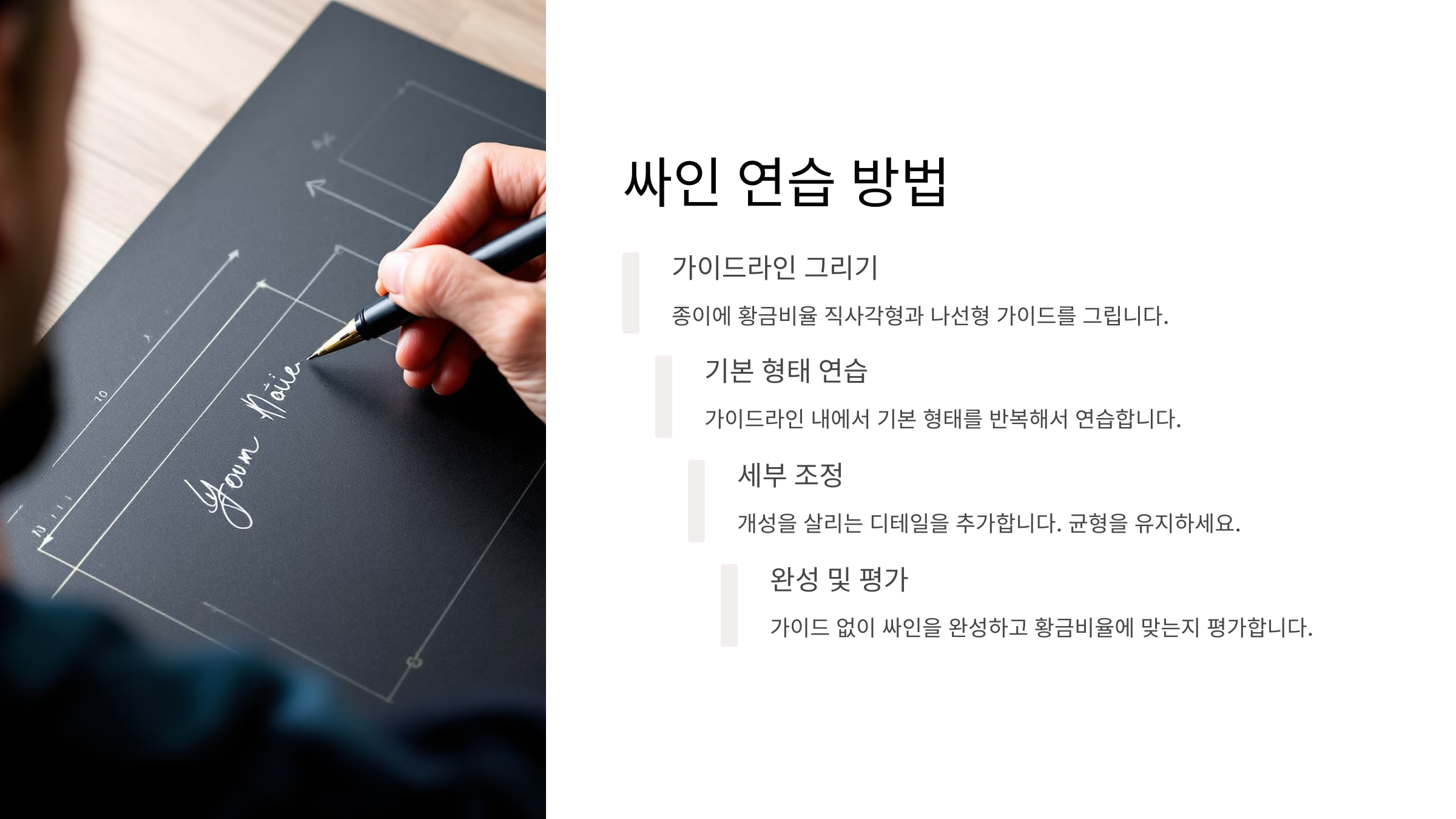
싸인도 디자인처럼 비율과 균형을 맞추면 더 멋져 보일 수 있어요! ✨ 특히 황금비율(1:1.618)을 활용하면 자연스럽고 조화로운 싸인을 만들 수 있죠. 🖊️
싸인이 너무 크거나 작으면 언밸런스해 보일 수 있고, 글자 간격이 너무 좁거나 넓으면 가독성이 떨어질 수 있어요. 그래서 싸인의 디자인 원칙을 알고 적용하는 것이 중요해요! ✅
그럼, 먼저 싸인의 황금비율이란 무엇인지부터 알아볼까요? 🔍
싸인의 황금비율이란? 📐
싸인의 황금비율이란 자연스럽고 균형 잡힌 서명을 만들기 위한 비율 원칙이에요. 우리가 흔히 알고 있는 1:1.618의 황금비율을 적용하면, 싸인도 훨씬 조화롭고 세련되어 보여요! ✨
이 황금비율은 자연과 예술, 건축, 디자인 등에서 흔히 발견되는 비율인데요. 레오나르도 다빈치의 '비트루비우스 인간', 피라미드, 유명 로고 디자인에도 적용됐어요! 🏛️
📌 싸인에서 황금비율이 적용되는 요소 ✅
요소 설명 싸인의 전체 크기 너무 크거나 작지 않도록 적절한 비율 유지 (1:1.618 적용) 이니셜과 나머지 글자 비율 이니셜이 전체의 약 61.8%를 차지하면 균형이 맞음 글자 간격 너무 붙거나 멀지 않도록 황금비율 간격 유지 곡선과 직선 조화 부드러운 곡선과 직선적 요소를 황금비율로 배치 이 원칙을 적용하면 더 세련되고 균형 잡힌 싸인을 만들 수 있어요! 그럼 이제, 싸인의 균형을 맞추는 방법을 알아볼까요? ⚖️
균형 잡힌 싸인 만들기 ⚖️
싸인이 멋지게 보이려면 균형이 맞아야 해요. 너무 기울거나, 글자가 한쪽으로 몰리면 비대칭적인 느낌이 들어요. 적절한 비율과 배치를 고려하면, 조화로운 싸인을 만들 수 있어요! ✅
📌 균형 잡힌 싸인을 위한 4가지 요소 🎯
요소 설명 예시 1. 중심축 맞추기 싸인의 중심이 기울지 않도록 일정한 축을 유지 "J.Kim" → J와 K를 동일한 높이로 정렬 2. 글자 크기 조정 이니셜이 너무 크거나 작지 않도록 황금비율로 조절 "H.Park" → H가 전체의 61.8% 차지 3. 글자의 흐름 너무 들쭉날쭉하지 않도록 글자의 흐름을 부드럽게 연결 "SeoHyun" → S와 H를 자연스럽게 연결 4. 비례 유지 글자 간 간격과 크기를 일정하게 맞춰야 안정감이 생김 "M.Lee" → M과 L의 간격을 일정하게 유지 균형 잡힌 싸인은 어떤 문서에서도 깔끔하고 세련된 인상을 줄 수 있어요. 그럼 이제, 자연스러운 글자 간격을 조절하는 방법을 알아볼까요? 📏
자연스러운 글자 간격 📏
싸인의 글자 간격이 너무 좁거나 넓으면 가독성이 떨어지고, 균형이 깨질 수 있어요. 따라서 적절한 간격을 유지하는 것이 중요해요! ✍️
글자가 너무 붙어 있으면 읽기 어렵고 답답한 느낌을 주고, 너무 멀리 떨어져 있으면 흐름이 끊긴 것처럼 보일 수 있어요. 적당한 간격을 유지하면 세련되고 정돈된 싸인이 완성돼요! ✅
📌 글자 간격을 조절하는 4가지 원칙 🔍
원칙 설명 예시 1. 균등한 간격 유지 글자 간격이 들쭉날쭉하지 않도록 일정하게 맞추기 "J. Kim" → J와 K 간격 일정하게 2. 첫 글자는 여유롭게 이니셜이나 첫 글자는 살짝 넓게 배치하면 자연스러움 "H. Park" → H 뒤 간격 약간 넓게 3. 마지막 글자는 붙이지 않기 마지막 글자가 다른 글자들과 너무 붙지 않도록 주의 "M. Lee" → e 뒤 여유 공간 4. 획이 겹치지 않도록 곡선과 직선이 겹치지 않게 적절한 공간 두기 "SeoHyun" → S와 e의 간격 유지 적절한 간격을 유지하면 가독성과 디자인이 동시에 향상돼요! 그럼 이제, 부드러운 필기 흐름을 만드는 방법을 알아볼까요? 🖊️
부드러운 필기 흐름 ✍️
싸인이 매끄럽게 보이려면 글자 간의 흐름이 자연스러워야 해요. 특히 곡선과 직선이 어색하게 끊기지 않도록 부드러운 필기감을 유지하는 것이 중요해요. ✅
너무 각진 싸인은 딱딱한 느낌을 줄 수 있고, 반대로 흐름이 없는 싸인은 연결감이 부족해 보일 수 있어요. 그래서 적절한 곡선과 직선을 조합하는 것이 핵심! ✨
📌 부드러운 싸인을 만드는 4가지 기술 🎨
기술 설명 예시 1. 곡선 활용 직선적인 싸인보다는 자연스러운 곡선을 가미 "J.Kim" → J를 곡선으로 부드럽게 2. 획의 연결 글자 간의 획이 자연스럽게 이어지도록 구성 "H.Park" → H와 P가 매끄럽게 연결 3. 리듬감 조절 일정한 속도로 싸인을 하여 자연스러운 흐름 유지 "SeoHyun" → 부드러운 손놀림 유지 4. 필압 조절 획의 강약을 조절하여 부드러운 느낌 연출 "M. Lee" → M의 시작은 강하게, 끝은 가볍게 이렇게 부드러운 흐름을 만들면 자연스럽고 멋진 싸인이 완성돼요! 그럼 이제, 디테일을 추가해 개성을 더하는 방법을 살펴볼까요? 🎭
디테일로 개성 더하기 🎭
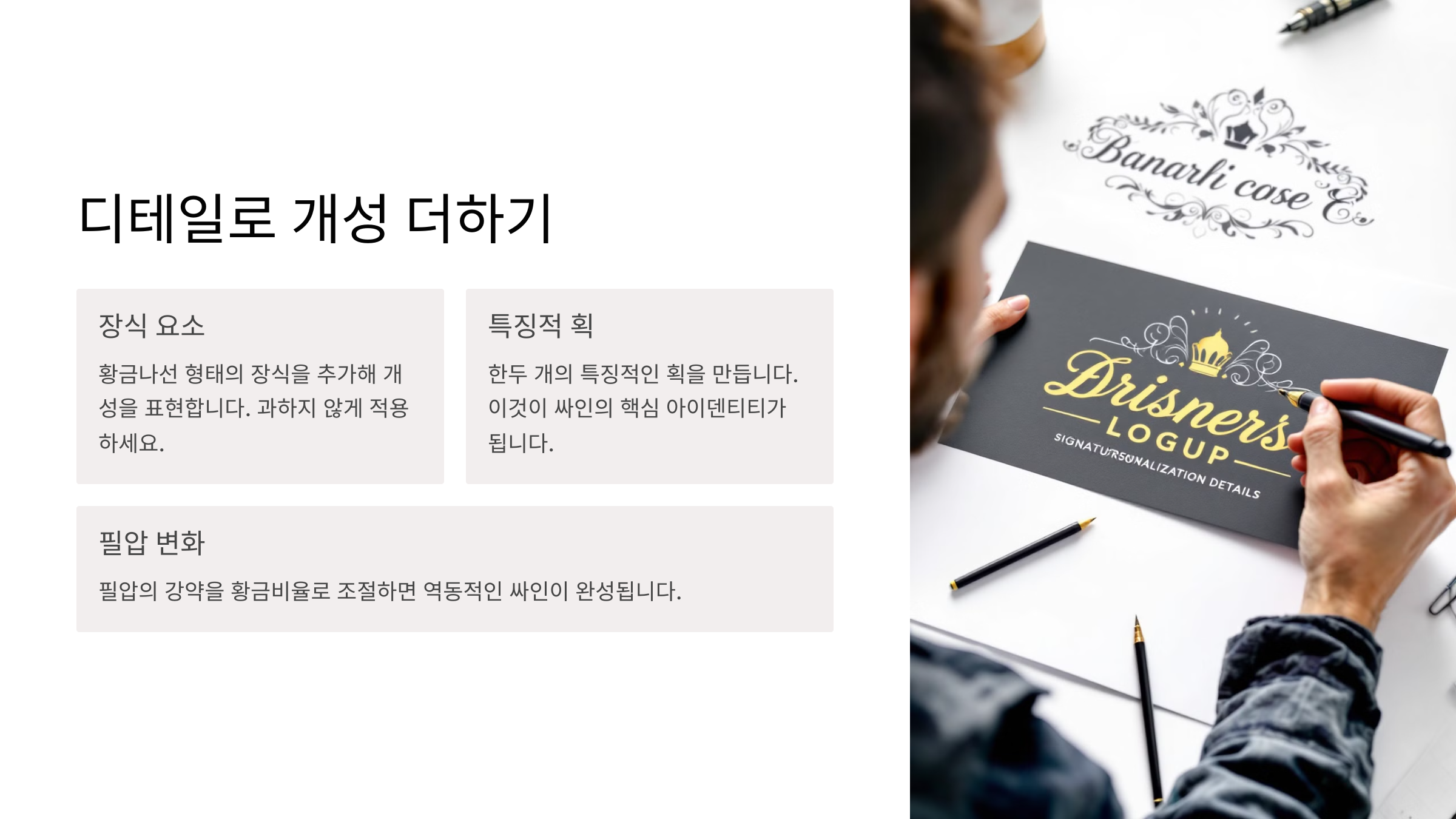
싸인은 단순한 서명이 아니라 자신만의 개성을 담을 수 있는 중요한 요소예요. 작은 디테일을 추가하면 더욱 독창적이고 특별한 싸인을 만들 수 있어요! ✍️
너무 흔한 스타일보다는 자신만의 개성을 살릴 수 있는 요소를 추가하는 것이 중요해요. 예를 들어, 밑줄, 별, 점, 독특한 곡선 등을 활용하면 싸인의 인상이 완전히 달라질 수 있어요! 🌟
📌 개성을 살리는 4가지 디테일 ✅
디테일 설명 예시 1. 밑줄 추가 싸인 아래 밑줄을 그어 강조 효과 주기 "J.Kim ⎯⎯" 2. 특수 기호 사용 별, 점, 물결 등 개성 있는 기호 추가 "H. Park ✨" / "S.Lim *" 3. 독특한 시작·끝 첫 글자나 마지막 글자의 스타일을 강조 "M.Lee ↘" / "D.Kim ↗" 4. 글자 변형 특정 글자를 길게 늘이거나 강조하여 개성 표현 "SeoHyun" → 'S'를 길게 이런 작은 디테일이 모이면 싸인의 개성이 더욱 돋보이게 돼요! 그럼 이제, 황금비율을 적용한 싸인의 예시를 살펴볼까요? 📜
황금비율 싸인 예시 📜
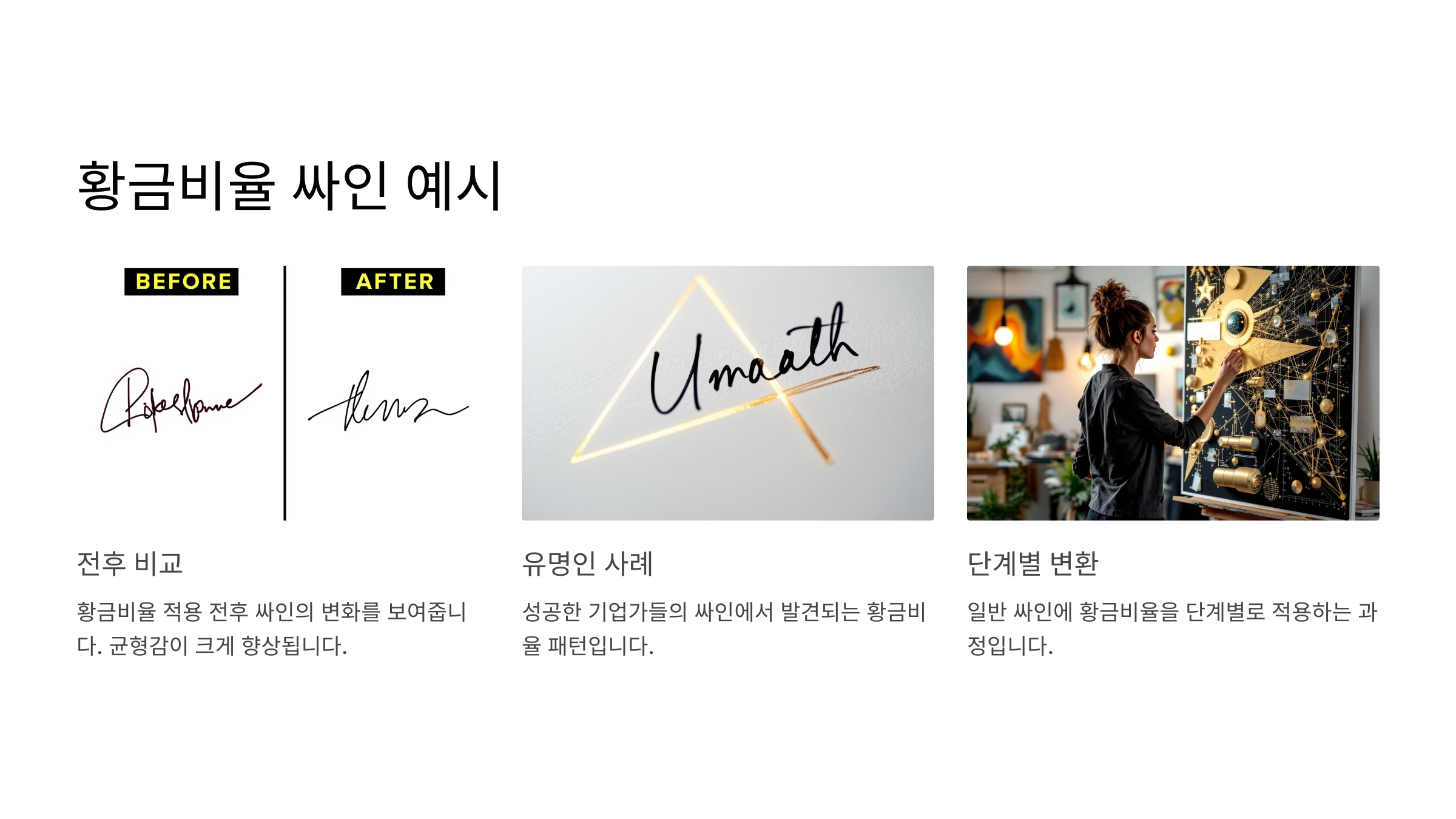
지금까지 싸인의 황금비율과 균형, 개성 있는 스타일을 만드는 법을 배웠어요. 이제 실제 예시를 보면서 어떤 싸인이 이상적인지 확인해 볼까요? ✨
📌 황금비율을 적용한 싸인 예시 ✅
싸인 스타일 설명 예시 1. 간결한 황금비율 싸인 이니셜과 이름이 적절한 비율로 조화된 싸인 "J. Kim" 2. 곡선과 직선 조합 부드러운 곡선과 직선이 조화를 이루는 싸인 "H. Park ↘" 3. 개성 있는 마무리 특별한 마무리 스타일(별, 밑줄 등) 추가 "S. Lim ✨" 4. 자연스러운 필기체 싸인 글자의 흐름이 부드럽게 연결된 싸인 "M. Lee" 이제 황금비율을 적용해 나만의 멋진 싸인을 만들어 볼 차례예요! 마지막으로, 싸인 디자인과 관련된 자주 묻는 질문(FAQ)을 정리해 볼게요. 📢
FAQ
Q1. 싸인의 황금비율은 왜 중요한가요?
A1. 황금비율(1:1.618)을 적용하면 균형감 있고 자연스러운 싸인을 만들 수 있어요. 너무 크거나 작지 않고, 가독성이 좋아지는 효과도 있어요! 📏
Q2. 싸인에서 가장 중요한 디자인 요소는?
A2. 균형, 흐름, 개성, 보안성이 가장 중요해요. 싸인이 너무 단순하면 개성이 부족하고, 너무 복잡하면 위조되기 쉬워요. ✍️
Q3. 싸인을 더 멋지게 만들려면?
A3. 곡선과 직선을 적절히 활용하고, 특수 기호(밑줄, 점 등)를 추가해보세요. 또한, 필기체 스타일을 변형하면 더욱 세련된 느낌을 줄 수 있어요. ✨
Q4. 싸인을 빠르게 하려면 어떻게 연습해야 하나요?
A4. 천천히 연습한 후 점점 속도를 높이는 방식이 좋아요. 손목과 손가락을 유연하게 풀어주면 속도감 있는 싸인을 만들 수 있어요. 💨
Q5. 싸인에서 글자 간격을 맞추는 방법은?
A5. 첫 글자는 살짝 넓게, 마지막 글자는 여유 공간을 두는 것이 좋아요. 또한, 이니셜과 이름의 크기를 적절히 조정하면 균형이 맞아요. ⚖️
Q6. 유명인의 싸인을 참고해도 될까요?
A6. 네! 빌 게이츠, 스티브 잡스, 일론 머스크 등의 싸인을 참고하면 싸인의 스타일과 균형을 배우는 데 도움이 돼요. 하지만 자신만의 개성을 추가하는 것이 중요해요! 🏆
Q7. 싸인을 꾸준히 연습하는 방법은?
A7. 하루 5분씩 짧게라도 반복해서 연습하는 것이 효과적이에요. 싸인을 녹화하거나, 다양한 필기구를 사용해 보면 스타일을 더 빨리 확립할 수 있어요! 🚀
Q8. 디지털 싸인과 손글씨 싸인은 어떤 차이가 있나요?
A8. 디지털 싸인은 태블릿이나 스마트폰에서 생성하는 전자 서명이고, 손글씨 싸인은 종이에 직접 작성하는 아날로그 방식이에요. 공식적인 문서에서는 전자 서명이 점점 더 많이 활용되고 있어요! 📱